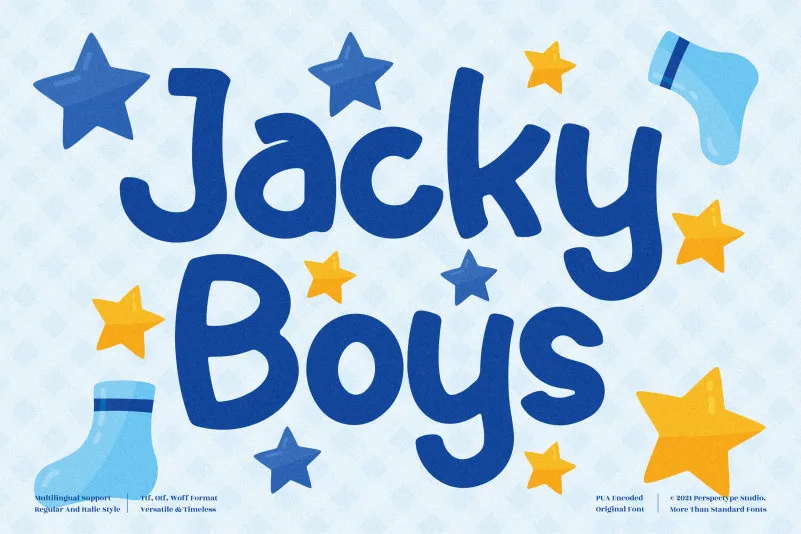
A fonte Jacky Boys é uma opção ideal para qualquer projeto que deseja transmitir um ar despreocupado e animado aos seus destinatários. Esta bela letra careta, com sua pitada de jovialidade, se assemelha a garotos da infância, sempre pronto para dançar em meio às festas e reunirções familiares. Se você está à procura de um design que reflete uma explosão de energia e alegria, Jacky Boys é o ideal escolhido. Além dos convites para festa e reuniões de amigos, esta fonte também se adapta perfeitamente às campanhas publicitárias, design gráfico e até mesmo à sua identidade visual corporativa. Seja sempre jovial e colorido com Jacky Boys, a fonte ideal para qualquer projeto que deseje um toque divertido e leve.